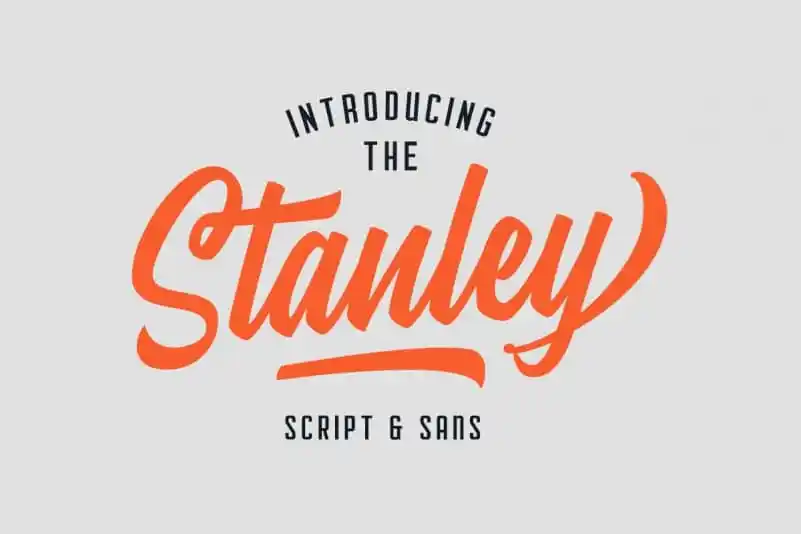
Através do design meticuloso de Hamilton, a Stanley Calligraphy Font é uma delírio para os amantes do estilo à mão. Inspirada no formato moderno e único de escrita, esta fonte apresenta um charme natural que se assemelha à forma como escrevemos livremente. Martype Co., responsável pela criação e partilha desta família de dois tipos de script, garantiram uma qualidade cuidadosamente elaborada. A Stanley Calligraphy Font é especialmente perfeita para os designers apaixonados por diferentes estilos. Através da sua versatilidade, este recurso gráfico pode ser usado em t-shirts, convites de casamento, design vintage e até mesmo nas criações dos seus logotipos ou qualquer projeto que necessite de um toque elegante. Com dois estilos disponíveis, esta fonte torna a criação de layouts e identidades digitais mais fácil e intuitiva, enquanto uma tipografia sans-serif adicional ajuda a criar design ainda melhor.